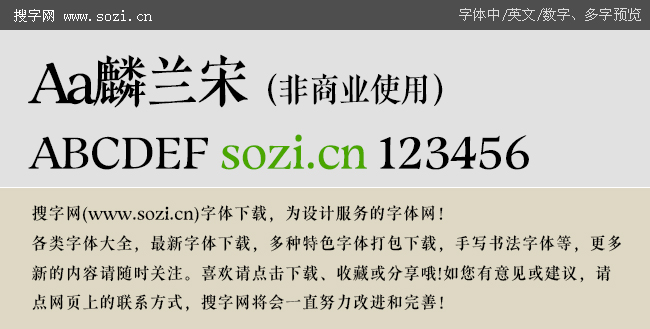
Aa麟蘭宋
搜字網(wǎng)給大家提供一款A(yù)a麟蘭宋(非商業(yè)使用)中文字體下載,Aa麟蘭宋是一款不錯(cuò)的藝術(shù)字體,字體筆觸適中,字形端正,具有很好的視覺感,適合應(yīng)用于藝術(shù)設(shè)計(jì)、平面宣傳設(shè)計(jì)、網(wǎng)頁(yè)設(shè)計(jì)、海報(bào)設(shè)計(jì)等應(yīng)用(此字體為個(gè)人非商用版,商用可以聯(lián)系QQ:1006760504)。